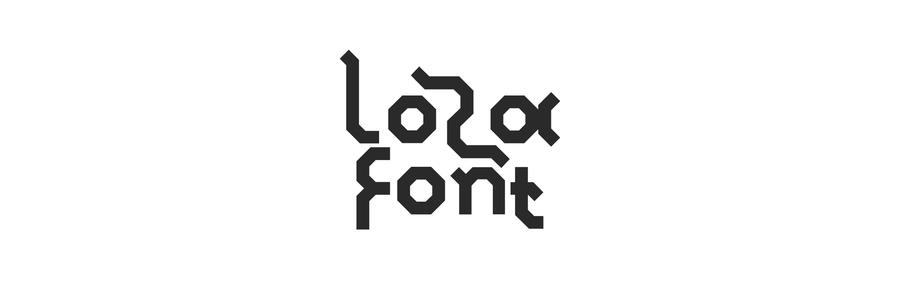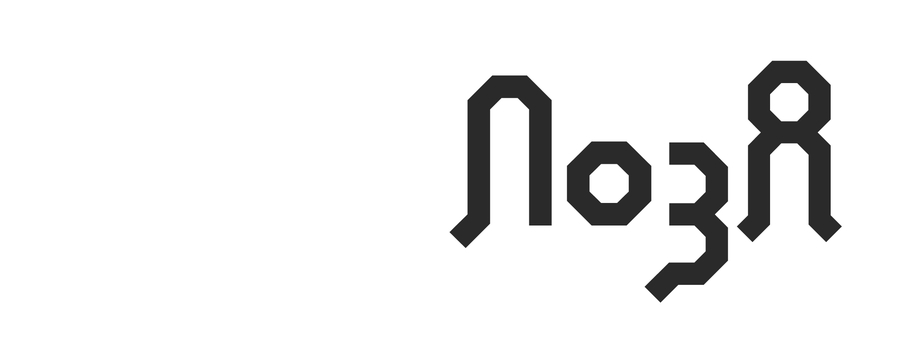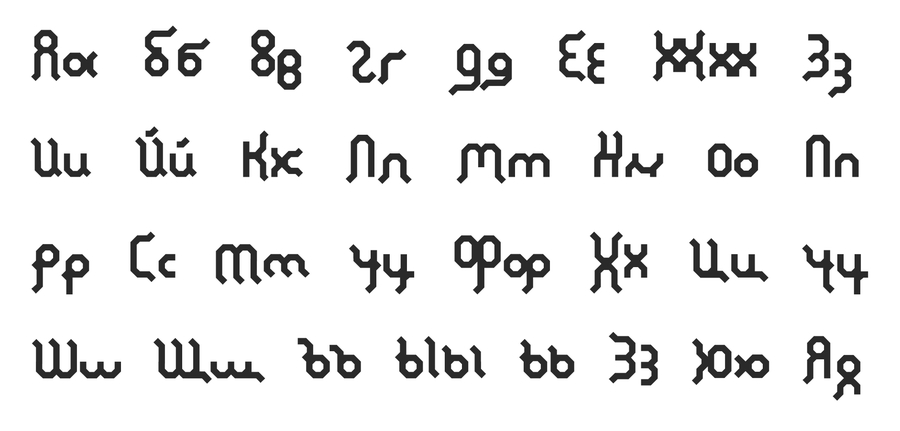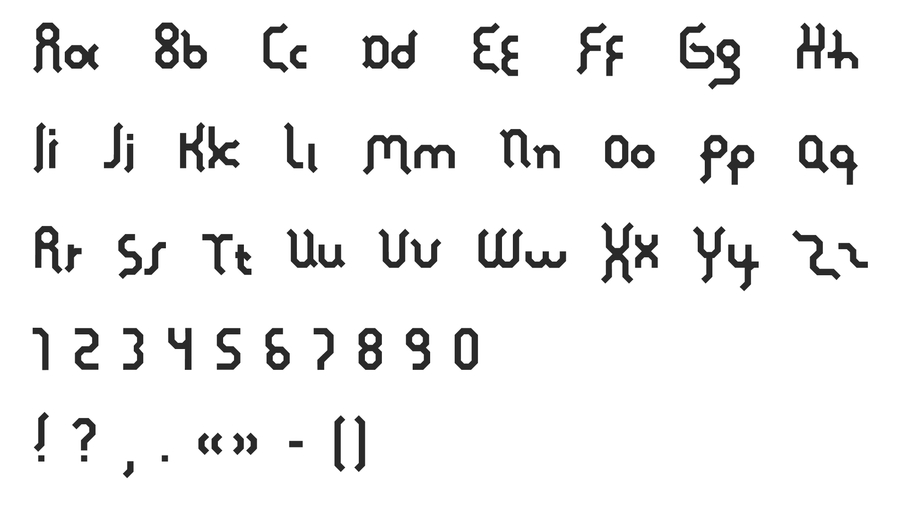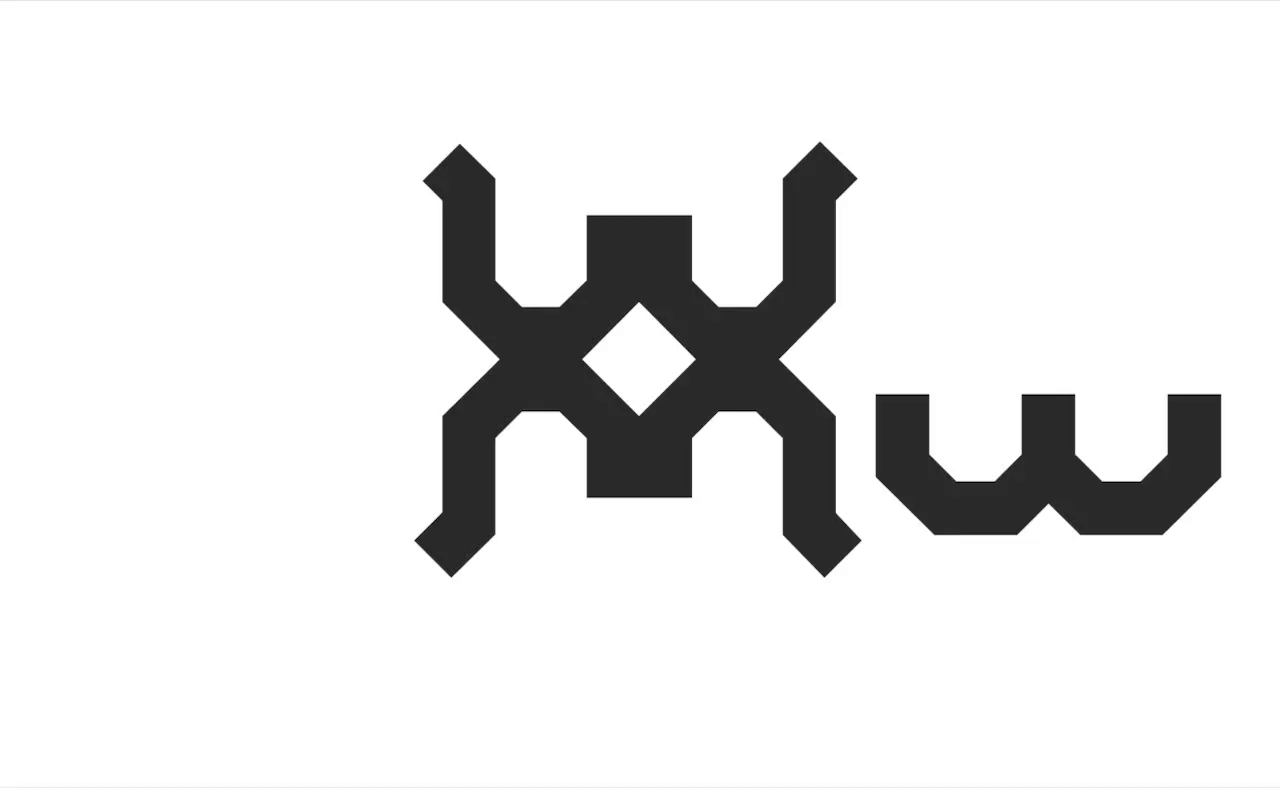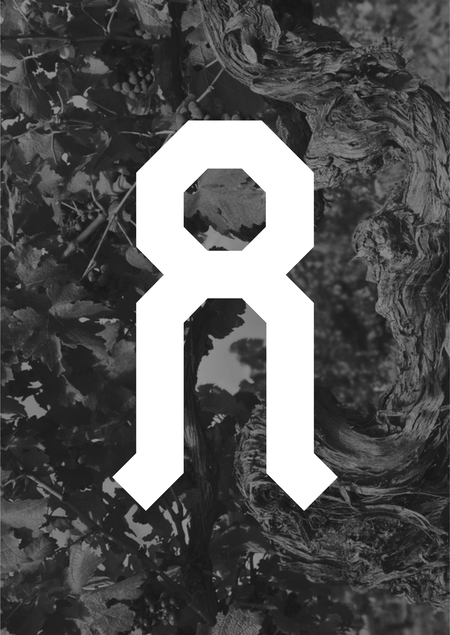
Loza — акцидентный модульный шрифт, вдохновленный геометрией изгибов лозы и витиеватых растений. Шрифт обладает угловатыми формами и выносными элементами, которые при написании между собой образуют сплетения.